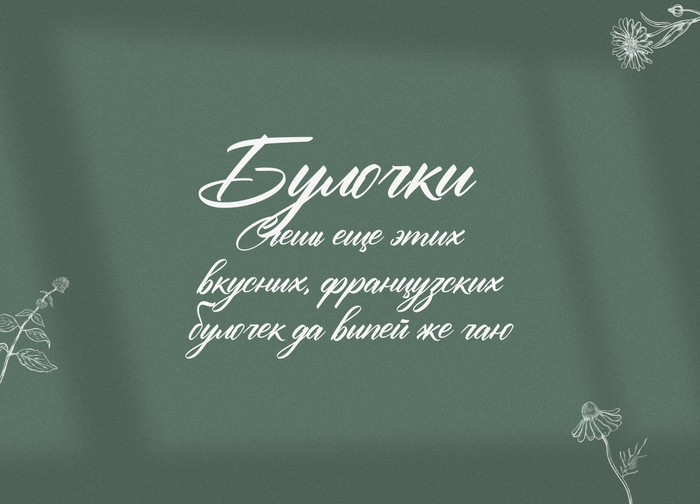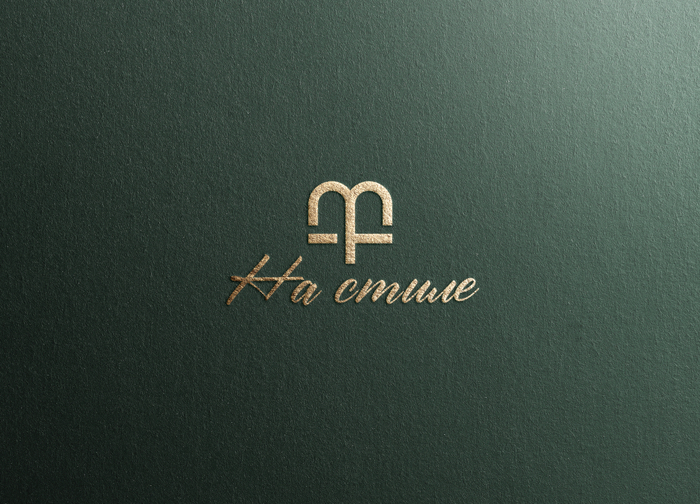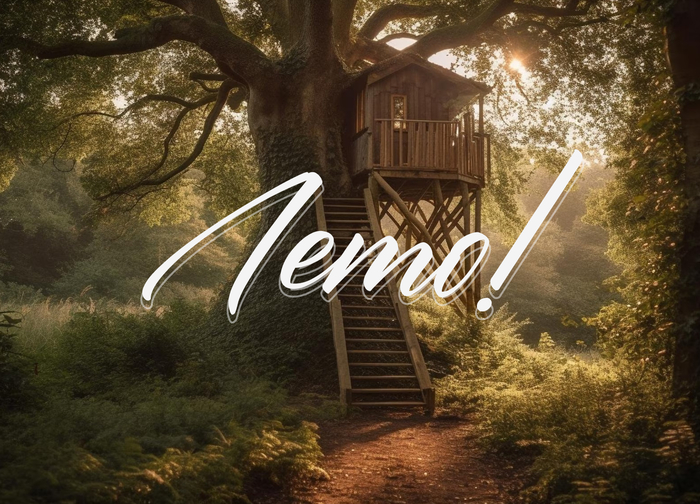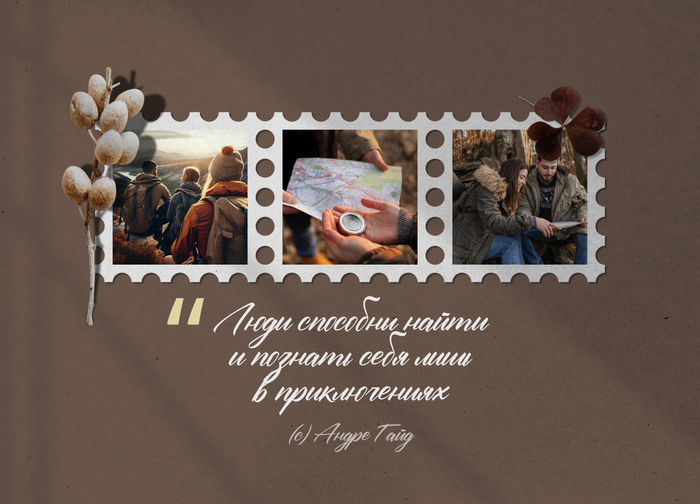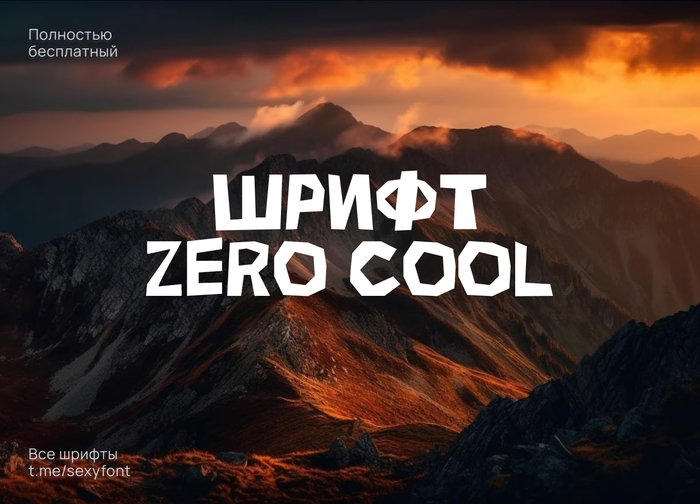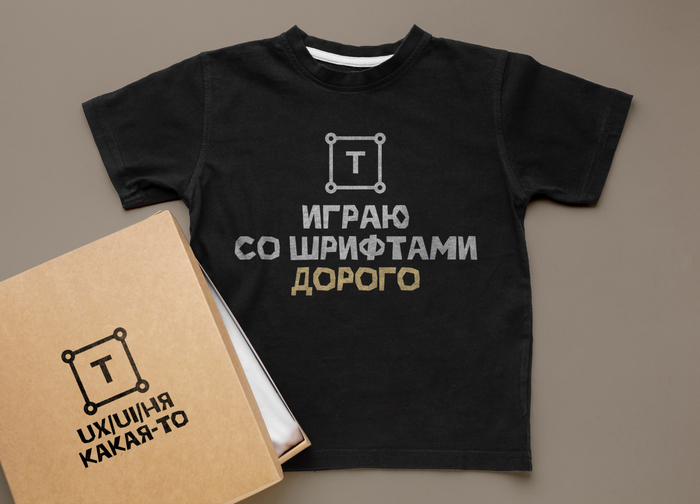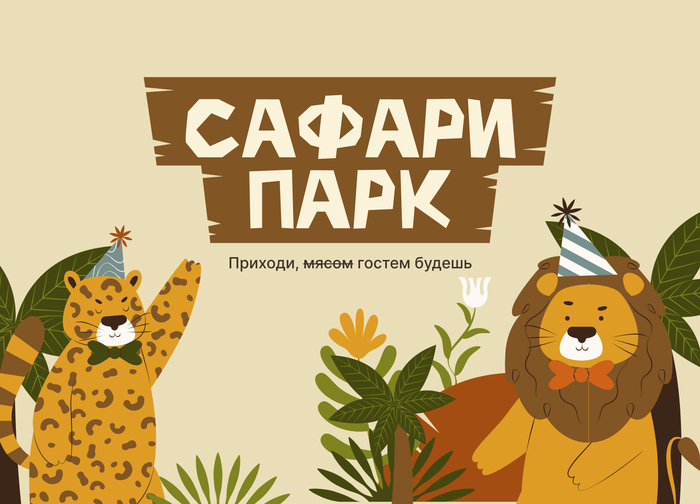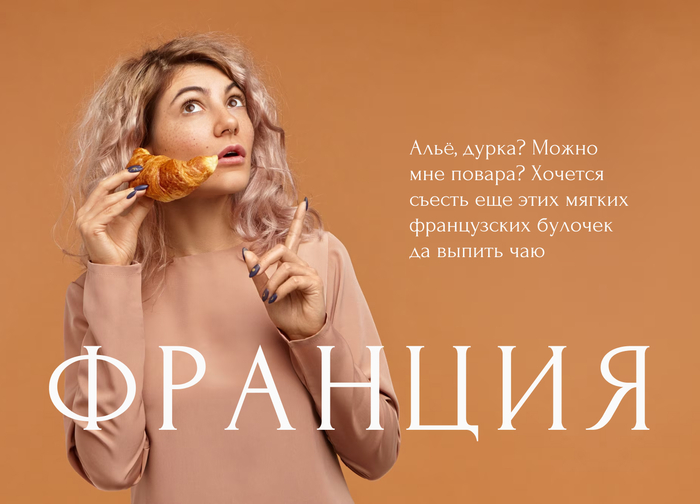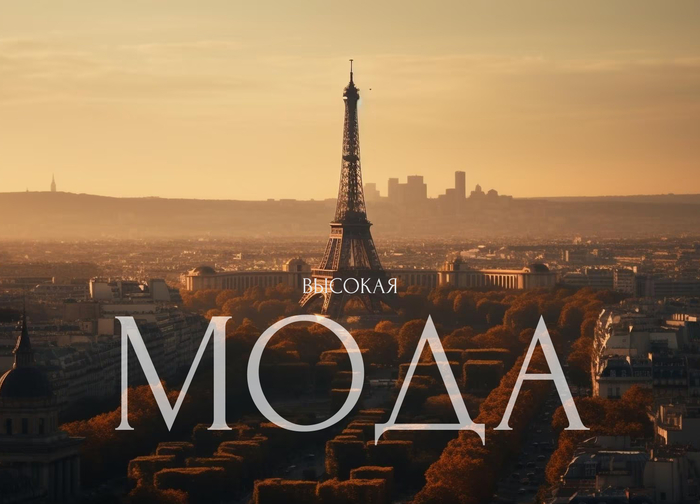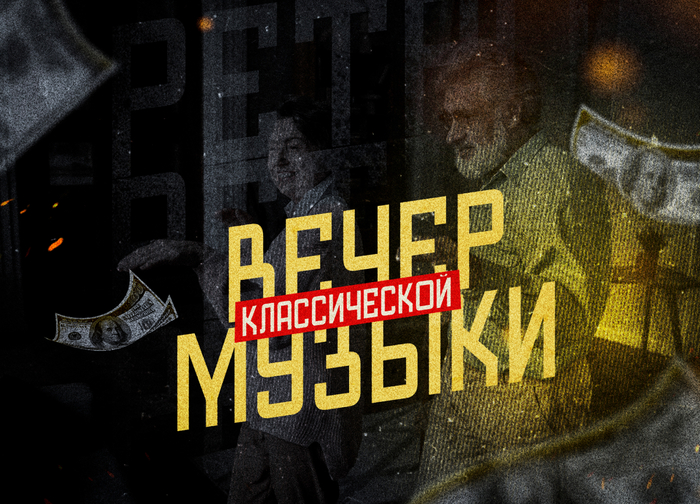
История клинописи
Сегодня не совсем про шрифт. А про важное начало, которое послужило основной для письма. Речь пойдет о клинописи. Расскажу ее значении в истории.
Дороу. Презентация Oldtimer. Неплохо читаемый шрифт для заголовок. Немного в ретро-стилистике. Поддерживает и кириллицу и латиницу)
Forum. Хорошо читаемая и бесплатная антиква с Гугл фонта. Минус только один – мало начертаний, а точнее оно одно, без жирностей, тонкостей и т.д А так, вполне неплохой вариантик. Как для заголовков, так и для небольших объемов текста.
Доделал новую презентацию) Zero cool. Декоративный, остроугольный и немного играющий шрифт. Бесплатно для личного и коммерческого использования. Спасибо за плюсы на прошлые посты) Огонь накидали.
Дороу. Ловите 7 пухлых шрифтов, которые выходили тут.
1. Peace sans. Жирный шрифт для создания оформительских надписей.
2. Shirota.
Заметный пухлый шрифт – широта. Отлично подходит для набора небольшго объема текст
3. Буба.
Ты посмотри какая Буба! Милый, пухлый шрифт.
4. Чехардаааа!
Классный, пухлый и вполне читаемый декоративный шрифт.
5. Банановый кирпич.
Яркий, пухлый, заметный банановый шрифтец. Отлично для баннеров и плакатов
6. Quacker.
Пухлый, рукописный шрифт) Идеально для тематик, связанных с едой.
7. Римма Санс.
Хороший, мощный шрифт)
Давно не было рукописных. Хороших бесплатных шрифтов в этом стиле крайне мало) Поэтому беру адаптации. Вопрос с точки зрения АП при переводе шрифта на кириллицу для меня остается открытым) На 99.9% уверен, что всем пофигу. Но смотрите на ваше усмотрение.
Сегодня у нас Ouvality (или Оуууу, Валите😅) Это кириллизация шрифта. Оригинал забугорный и платный)
Конничива! Kashima.
Автор оригинального шрифта, дизайнер из Индонезии Panggah Laksono
Давно не было антиквы. И вот этот час настал. Опытные дезигнеры знают этот шрифт на зубок) Многим уже 100% приелся и снится по ночам. Я сам сделал с ним десятки проектов. Периодически оставляю его и возвращаюсь вновь. Люблю его.
Итак, Дамы и господа. Стандартный, но от этого не менее красивый PLAYFAIR DISPLAY мазафака!!! Теперь и вариативный вариантик.